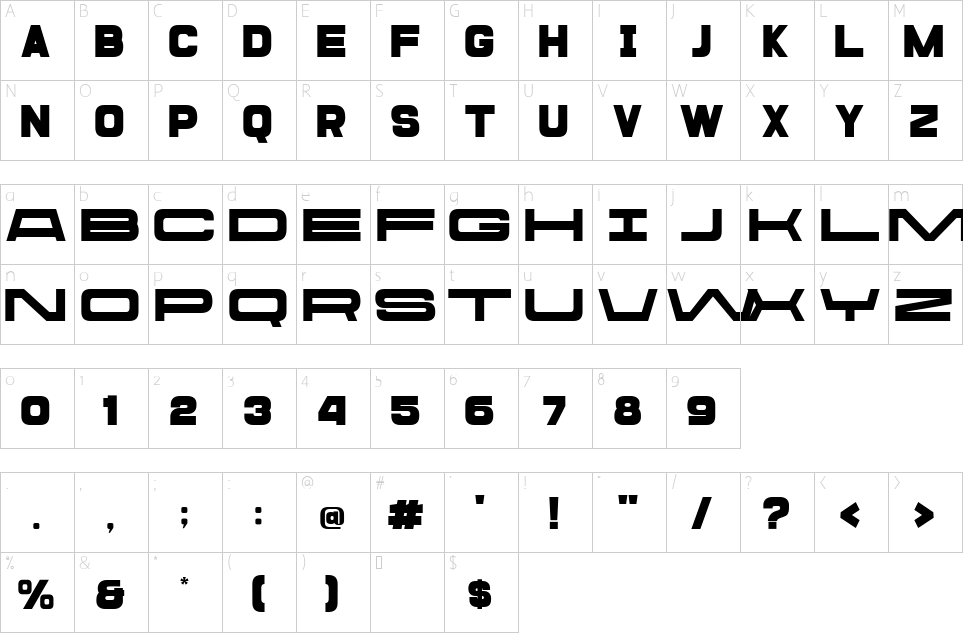
Aron Wergel é uma fonte minimalista e sofisticada projetada pelo designer madeDeduk, disponível gratuitamente tanto para Windows quanto para Mac. Esta fonte atua como um elo perfeito entre modernidade e elegância, adequada para um amplo leque de aplicações, desde designs gráficos até criação de logotipos. O design minimalista de Aron Wergel destaca-se por sua simplicidade e clareza, permitindo que a linguagem textual seja acentuada sem perder sua essência. Com uma instalação limpa e rápida, Aron Wergel oferece uma experiência satisfatória para os designers que buscam uma fonte de alta qualidade e versátil sem pagar uma centinha. O design da fonte foi pensado para atender aos mais diversos gosto e preferências, desde um uso mais tradicional até estilos mais modernos. Aron Wergel é perfeito para quem busca uma opção gratuita para suas necessidades gráficas, sem sacrificar a qualidade e a elegância.